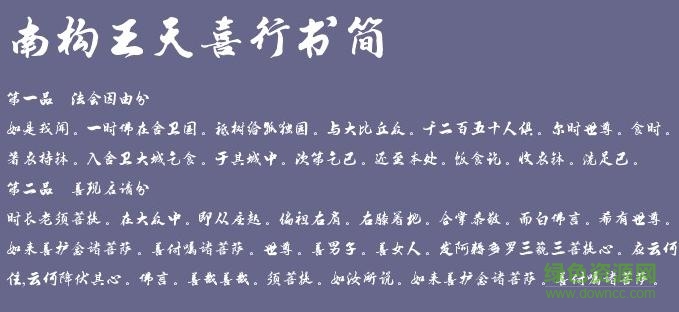
南構(gòu)王天喜行書簡體字體
南構(gòu)王天喜行書簡體是一款由王天喜先生創(chuàng)作的行書字體,字形漂移流暢,筆墨之間揮灑大師豪氣,行文儒雅、大氣。還等什么,快來綠色資源網(wǎng)踴躍下載使用!
南構(gòu)王天喜行書簡是由王天喜老師書寫創(chuàng)作的字體,毛筆行書風(fēng)格,行云流水,大氣自然。